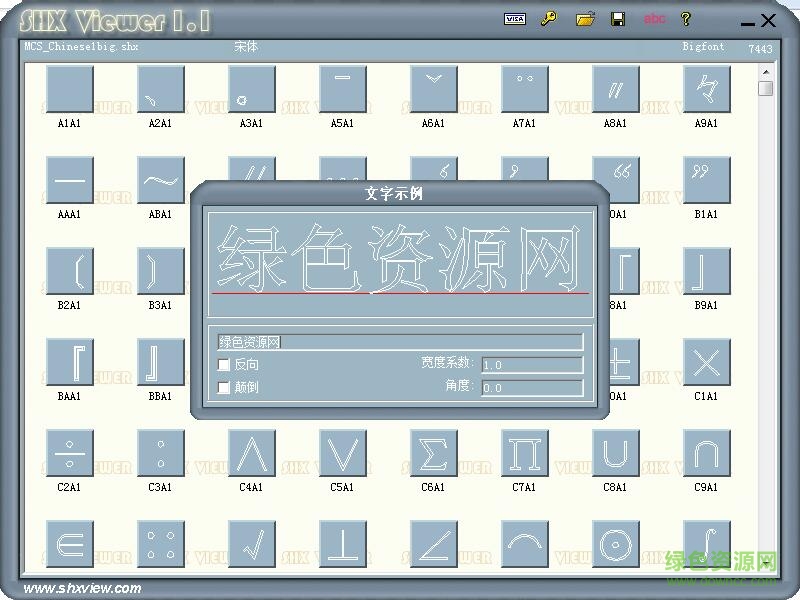
mcs chinese1big.shx是一種和華文彩云字體風(fēng)格相似的字體文件??梢宰鳛榻ㄖO(shè)計(jì)使用。如果您的系統(tǒng)中提示mcs chinese1big.shx字體不存在,是無(wú)法正常查看cad圖紙的。需要的用戶歡迎下載使用。
mcs chinese1big.shx字體能夠在CAD中進(jìn)行輸入和寫(xiě)文字,讓用戶更好的標(biāo)注CAD中的圖紙。是建筑行業(yè)用戶查看圖紙必備的字體文件。